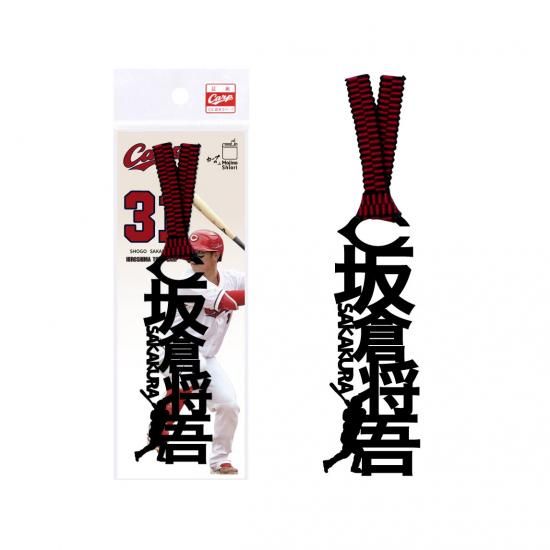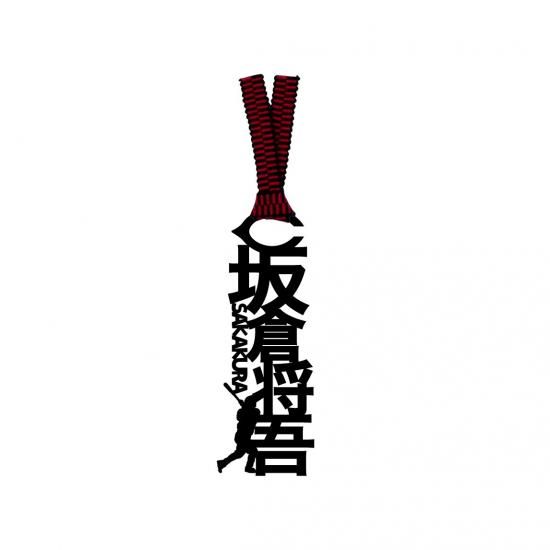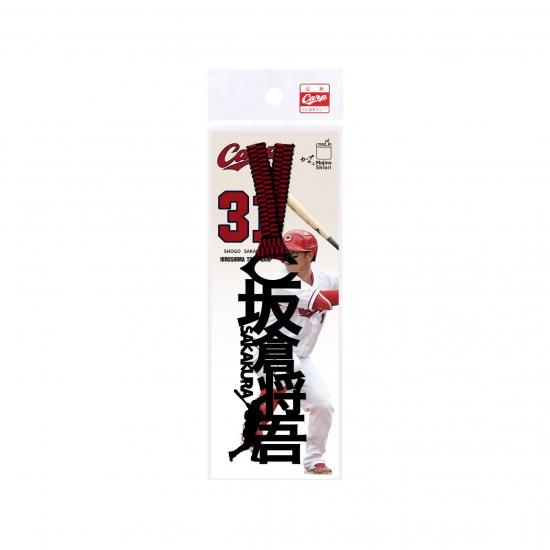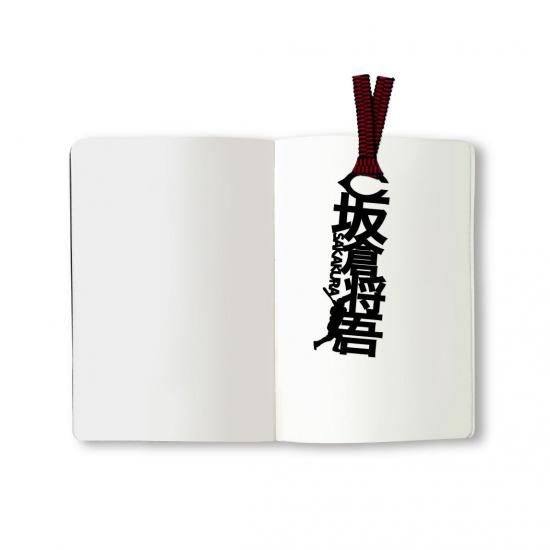
文字のカープのしおり2025「坂倉将吾」
今年の文字のカープのしおりは、日本の伝統的な紐である真田紐とシルエットのマッチアップ。
本や手帳で、カープ選手が、打って守って大活躍!あなたのことを一瞬たりとも忘れることはございません。
推しをはさんで、推しとともにカープな日々をお過ごしください。シーズン中も、オフシーズンも、本や手帳の間にカープ愛をどうぞ。
木材パルプや綿を原料とした環境素材を採用し、耐久性・耐水性に優れたファイバー紙の特徴を活かすことで、
言葉がフォントごと切り取られたような巧緻で美しい『文字のしおり』のデザインが実現しています。